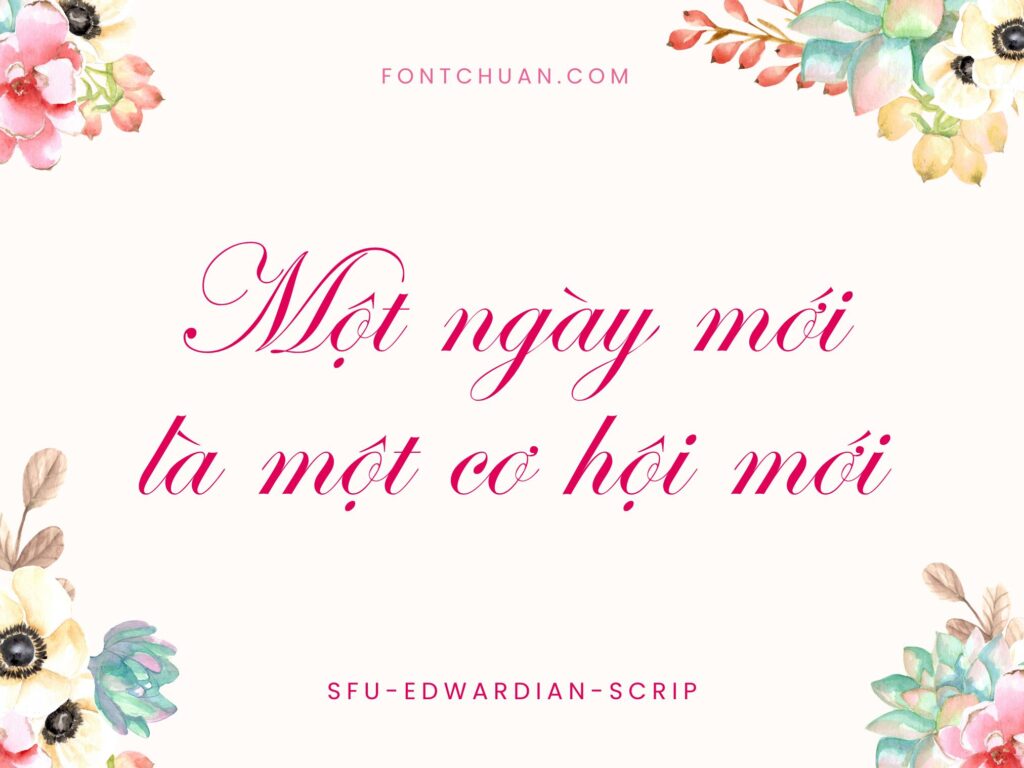
Font UTM Edwardian Việt Hóa
UTM EdwardianKT là phiên bản Việt hóa của font chữ Edwardian Script ITC, một Font Script thanh lịch được thiết kế bởi Edward Benguiat và phát hành bởi International Typeface Corporation (ITC). Font này nổi bật với các ký tự viết tay mềm mại, đường nét uyển chuyển và tinh tế, tạo cảm giác sang trọng và cổ điển. Phiên bản Việt hóa đã được thực hiện bởi Công ty TNHH Vitoen, hỗ trợ đầy đủ tiếng Việt cùng hơn 100 ngôn ngữ khác. Đây là một trong những font được cộng đồng thiết kế sưu tầm và chọn lọc nhằm đáp ứng nhu cầu đa dạng trong thiết kế.
UTM EdwardianKT có cấu trúc chữ với các nét thanh mảnh và độ nghiêng nhẹ, đặc trưng của dòng Font Handwritten, giúp mang lại sự mềm mại, tự nhiên và tinh tế trong từng đường nét. Font này phù hợp cho các ứng dụng như thiết kế thiệp mời, chứng chỉ, bằng khen, tiêu đề và các ấn phẩm in ấn yêu cầu sự trang trọng và nghệ thuật. Các ngành nghề như quảng cáo, giáo dục, công nghệ và bất động sản có thể tận dụng UTM EdwardianKT để tạo điểm nhấn độc đáo trong thiết kế.